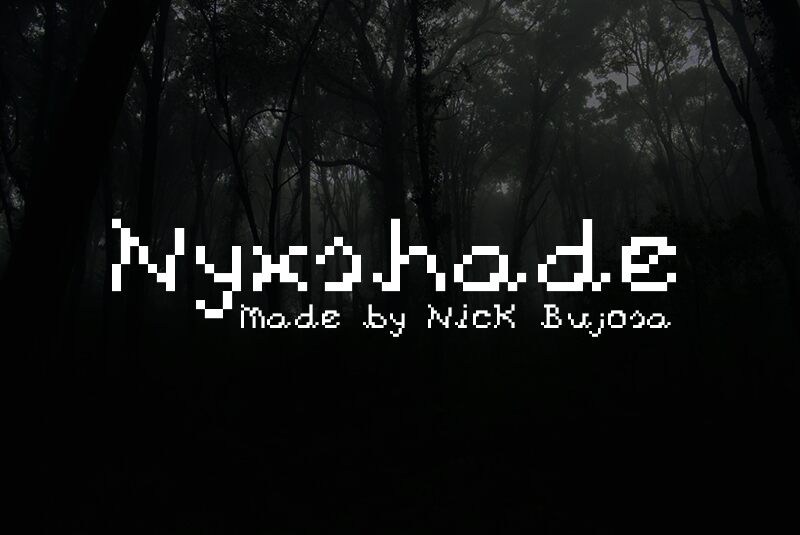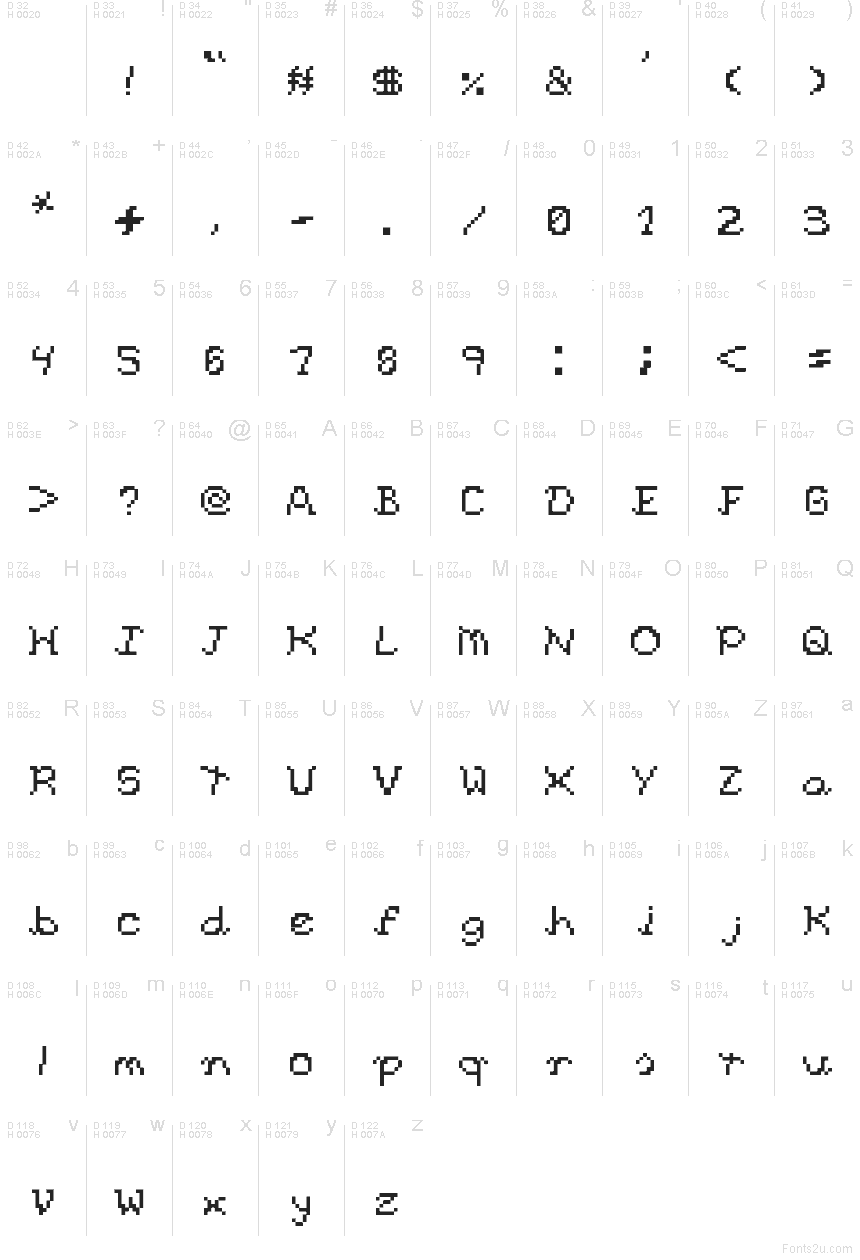
Nyxshade_Pixel Tipo de letra
Nyxshade Pixel é uma fonte bitmap gratuita com uma atitude espinhosa e noturna. As suas letras parecem esculpidas numa grelha grossa, misturando diagonais irregulares com curvas robustas, criando uma textura que evoca tanto o medieval como a estética das primeiras telas digitais.
Isso torna-a perfeita para logótipos de jogos, posters de fantasia sombria, fanzines, gráficos de streaming e títulos onde uma fonte gratuita pode definir o ambiente antes de adicionar mais elementos. Também funciona muito bem para títulos curtos e monogramas, pois os ziguezagues afiados e os cantos quebrados conferem, mesmo a poucas letras, uma presença densa e emblemática.